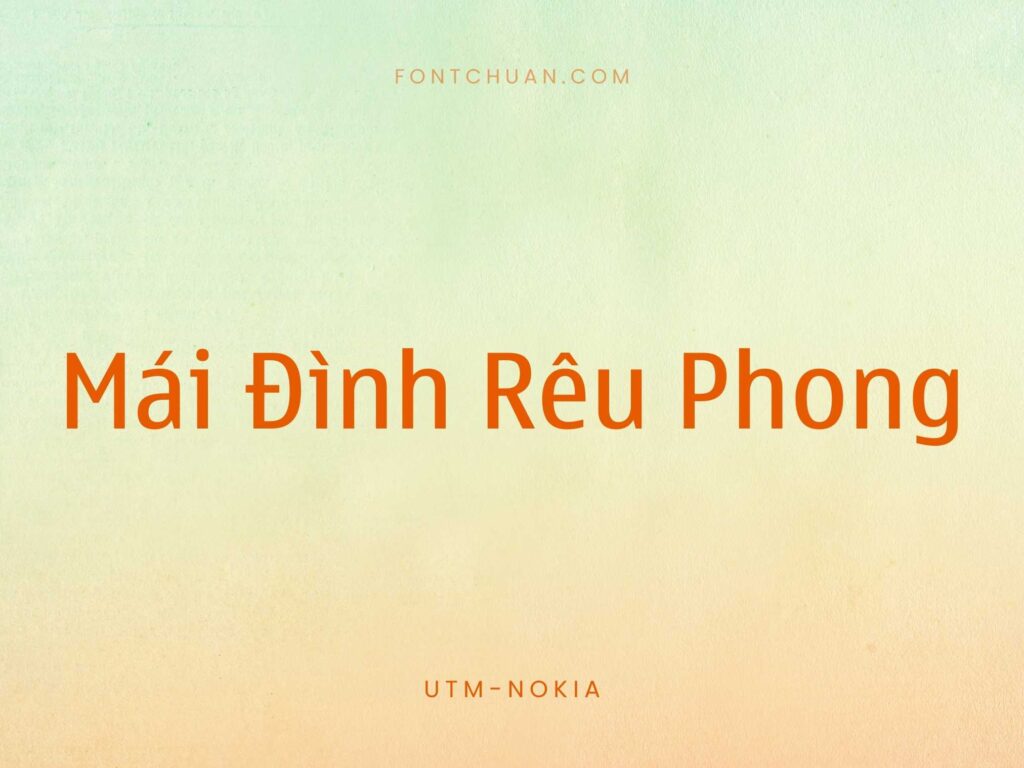
UTM Nokia là một font chữ sans-serif hiện đại, được thiết kế với cấu trúc hình học mạnh mẽ và rõ ràng. Các ký tự có độ rộng đồng đều và đường nét nhất quán, tạo nên vẻ ngoài chắc chắn và ấn tượng. Font này đã được Việt hóa, hỗ trợ đầy đủ tiếng Việt, giúp mở rộng khả năng sử dụng trong nhiều lĩnh vực thiết kế. Thành viên của Font Chuẩn đã sưu tầm và giới thiệu font này nhằm đáp ứng nhu cầu của bạn đọc, cung cấp nguồn tham khảo chất lượng và ứng dụng thực tế vào các dự án thiết kế.
Về đặc điểm thiết kế, UTM Nokia có các đường nét rõ ràng, độ dày đồng đều và phong cách hiện đại. Font này phù hợp với nhiều ứng dụng như thiết kế thương hiệu, tài liệu chuyên nghiệp, website, trình bày văn bản, bảng hiệu và biển quảng cáo. Các ngành nghề như quảng cáo, giáo dục, công nghệ và thiết kế thương hiệu có thể tận dụng font này để tạo điểm nhấn và tăng tính chuyên nghiệp trong các sản phẩm thiết kế. Đặc biệt, với các tài liệu giảng dạy, sách giáo khoa, bài giảng hay các ấn phẩm học tập, UTM Nokia còn có thể được sử dụng như một Font chữ giáo dục lý tưởng, vừa rõ ràng, dễ đọc, vừa mang phong cách hiện đại và tinh tế, hỗ trợ việc truyền đạt thông tin hiệu quả.